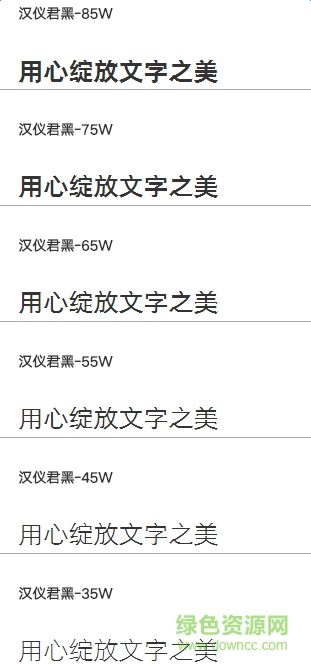
漢儀君黑體是漢儀系列正規(guī)細(xì)黑字體軟件,該字體粗細(xì)均勻,筆畫(huà)一絲不茍適合正式場(chǎng)合的設(shè)計(jì)應(yīng)用,用來(lái)練書(shū)法再合適不過(guò)了,歡迎大家來(lái)綠色資源網(wǎng)踴躍下載哦!
漢儀君黑體是一款非常穩(wěn)重的手寫(xiě)字體,筆畫(huà)流暢、厚重。字形工整有力,筆生蓮花。